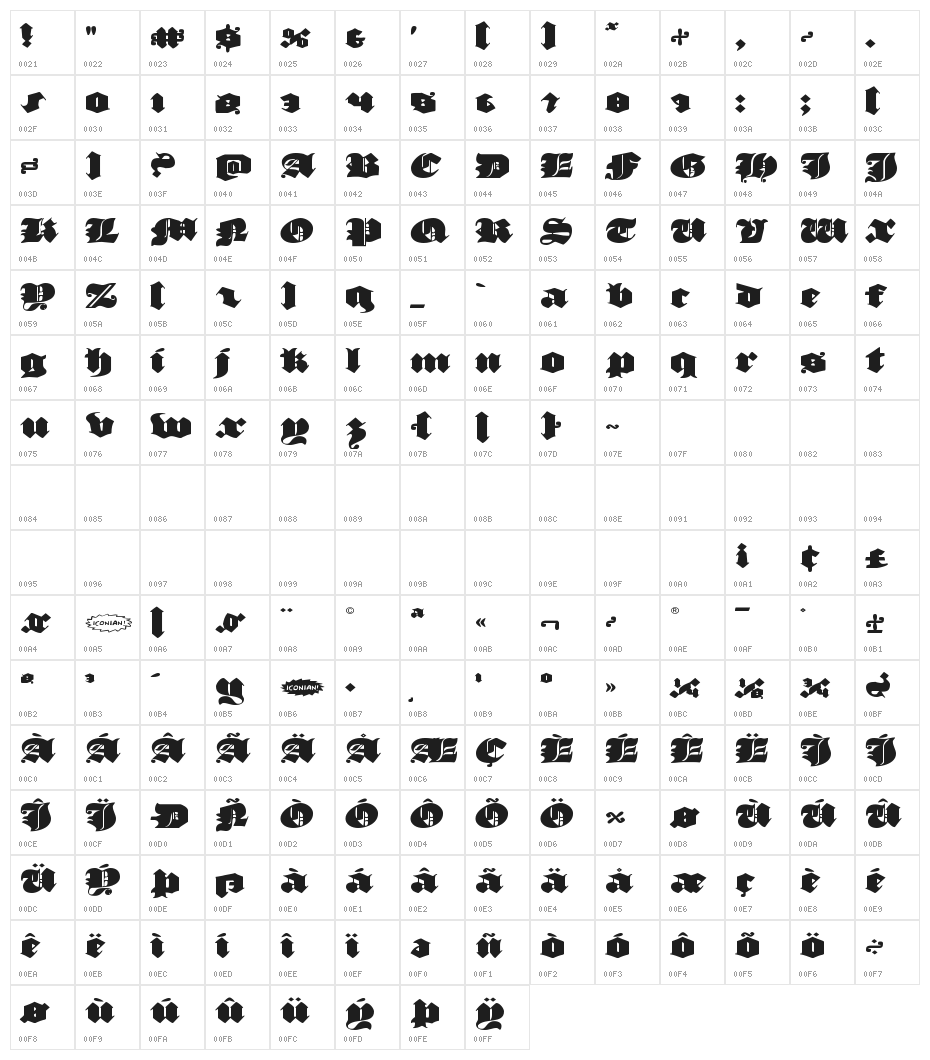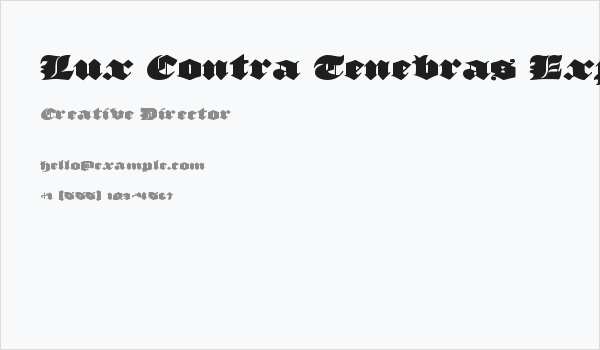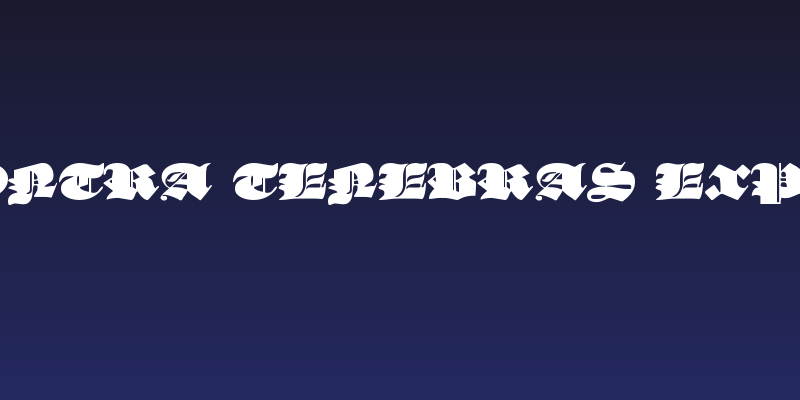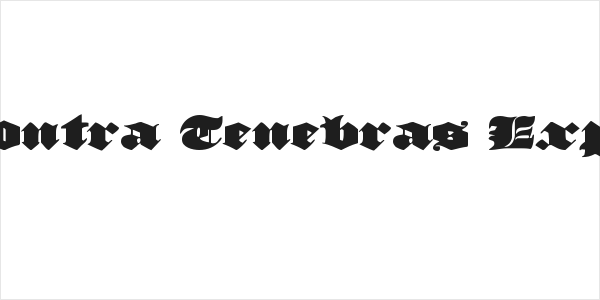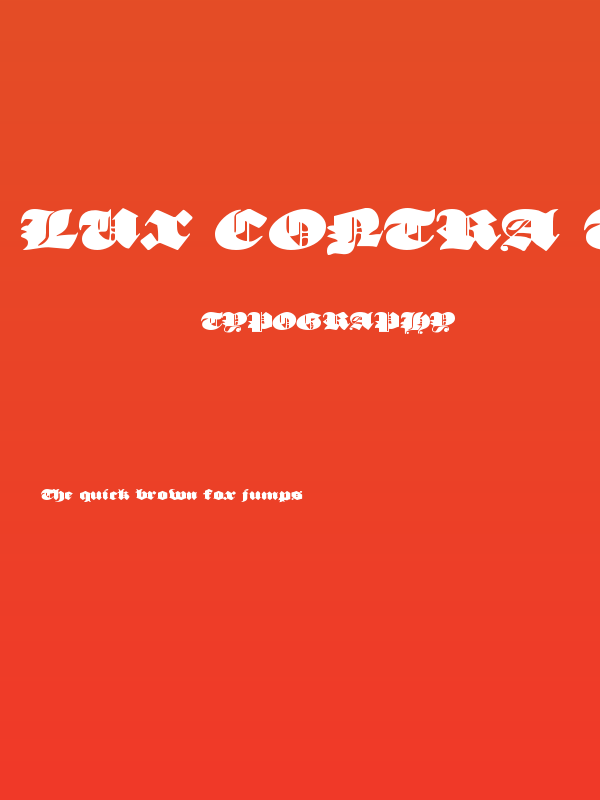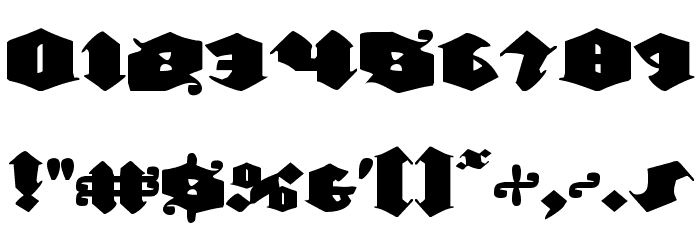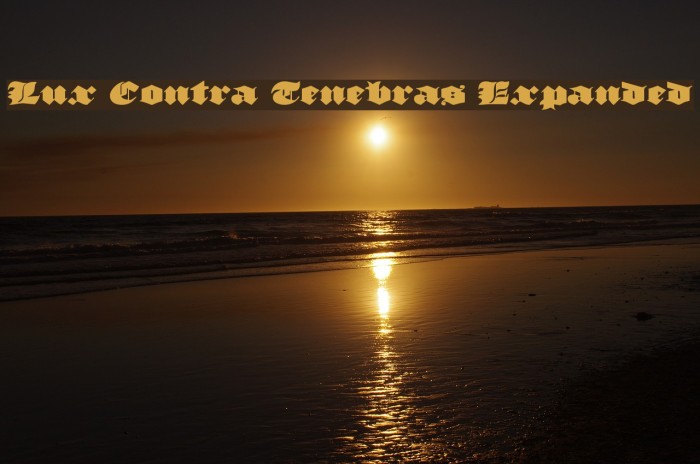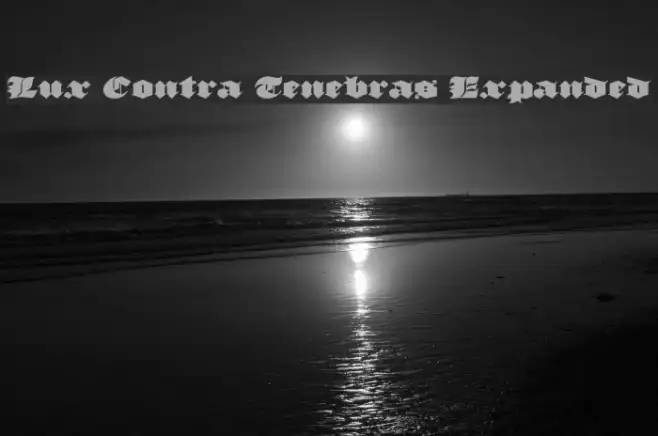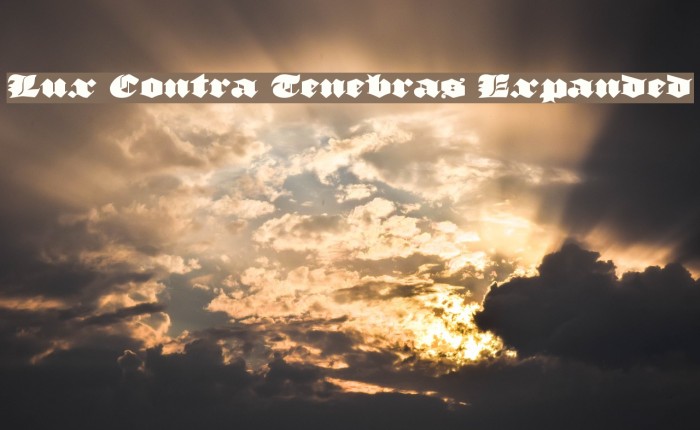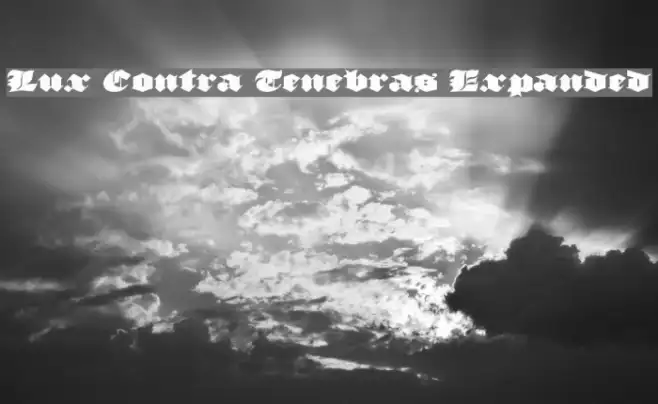
Lux Contra Tenebras Expanded Font
| Estilo general | Gothic, Medieval |
| Caso de uso | Headlines, Logos, Decorative text |
| Proyectos propuestos | Ideal for use in historical or fantasy-themed designs, such as book covers, posters, and branding for events or products that want to convey a sense of tradition and grandeur. |